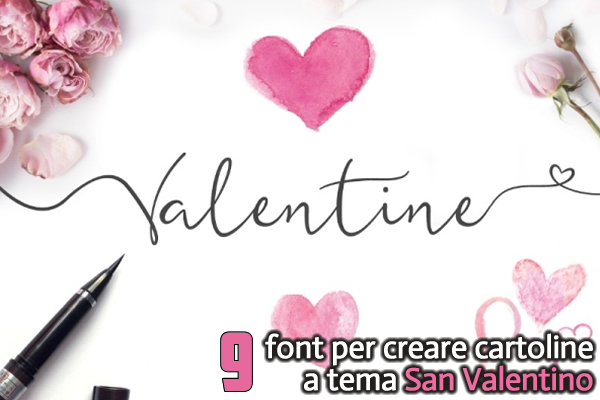
Vi segnalo sul sito SDR una bella raccolta di font gratuiti a tema San Valentino per progettare e creare biglietti di auguri.
La raccolta è composta da un totale di 20 font bellissimi e romantici, di cui 9 gratis perfetti per tutti i propri progetti a tema San Valentino come biglietti, poster con citazioni d'amore, volantini per feste, ecc.
La raccolta include diversi tipi di caratteri: scrittura a mano elegante, caratteri con ornamenti, caratteri stile pennello, caratteri sottili e altro ancora.
9 font per creare cartoline a tema San Valentino